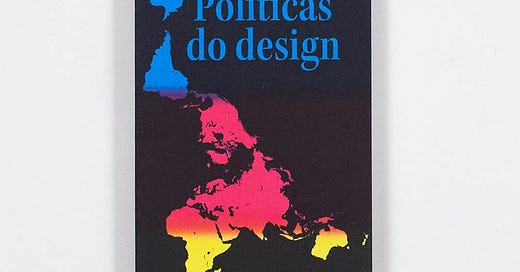
Tipo Aquilo #27 – Políticas do Design
A palavra “política” não deve ser usada de forma leviana. No nosso cenário midiático, cada vez mais polarizado, muitas pessoas dizem ter liberdade para serem apolíticas ou para ficarem de fora da política, como se existisse uma terra mágica para onde fosse possível fugir, sem sofrer o peso da opressão e da violência. Seria ótimo, mas infelizmente não existe um lugar assim.
Essa introdução faz parte da edição brasileira de “Políticas do Design”, de Ruben Pater, lançada pela Editora Ubu. A newsletter de hoje é uma espécie de resenha do livro, como pretexto pra falar aqui de toda a agitação social vivida no mundo, e alguns desdobramentos que acertaram em cheio até o mundinho da tipografia. Por ora, vamos ao livro.
A julgar pelo título, o leitor pode pensar que trata-se de um manifesto partidário de direita ou esquerda, disfarçado de guia de design. Ele não é. Também não quer dizer que ele seja um livro isentão ou simpático ao dois-ladismo. As políticas que aborda são as práticas e habilidades que o designer deve ter para projetar num mundo realmente global, atentando-se ao que ”global” significa de fato: uma grande civilização com várias religiões, idiomas, escritas, histórias, etnias e biomas vivendo num geoide. Por isso, ele aborda vários tópicos organizados entre os fundamentos da comunicação visual, e como esses tópicos funcionam em culturas diferentes.
Cada capítulo é breve — saltando entre erros, acertos e curiosidades de produção gráfica, branding e design digital — e o livro conta com várias adições e atualizações desde a primeira edição impressa. Com isso, ele consegue oferecer uma leitura rápida e assertiva em pouco mais de 180 páginas, e cada capítulo traz uma nova provocação sobre o que significa fazer design para um mundo global e menos centrado em Europa e América do Norte. É um primeiro passo interessante para uma conversa que estará mais frequente nos próximos tempos, a de descolonização do design.
Pense que o design, ao longo da história, cercou-se de um pensamento eurocêntrico que determina o que é design e quem pode dizer que faz design. O resultado é que, como vários campos de conhecimento, a história do design é um grande rolê de homens brancos. É difícil encontrar referências negras de design, por exemplo, e também é difícil que sejam entendidas como design outras atividades de produção e expressão visual em série feitas fora das capitais econômicas. Deveria ser mais fácil hoje, mas estamos em 2020 e ainda falamos de gente que quer estipular como e quando quer ser mais tolerante a diversidade.
Percepções baseadas em estereótipos de outras culturas também são maus exemplos na tipografia. Um exemplo é a Neuland, fonte criada em 1923 pelo alemão Rudolf Koch como uma versão moderna de escrita blackletter. Essa fonte tornou-se uma escolha comum para embalagens de cigarros e letreiros de circos, dando à fonte uma conotação “exótica” e “selvagem” o suficiente para que uma releitura de escrita gótica alemã pareça uma tipografia étnica africana. Enquanto a comunidade afro-americana produzia revistas e capaz de jazz usando fontes convencionais, os brancos ainda se divertiam com seu pastiche de arte africana, e reforçavam estereótipos com tipografias étnicas também com chineses e árabes.
Quem se envolve com ativismo no design muitas vezes trabalha em estúdios comerciais durante o dia e cria memes e imagens ativistas à noite. Não se trata de um caso de esquizofrenia, como se o designer se dividisse entre uma personalidade política e outra apolítica, mas sim de uma tática de sobrevivência para manter a saúde física e mental. Não dá para separar o design da vida pessoal, da mesma maneira como não dá para separar o design da política.
Algo que o livro aborda em vários exemplos, mas muito designer ainda sai da academia sem esse conhecimento, é que mesmo as menores decisões tomadas num processo de design são políticas, porque as relações humanas são essencialmente políticas. Escolhas de cores, fontes, redação, imagens, materiais e meios, são tomadas com base em vieses bem definidos e alinhados aos valores de pessoas e/ou organizações que visam influenciar e persuadir outras pessoas. Isso é política tanto quanto são as decisões de políticos que interferem no design. É discurso feito em imagem. Num mundo em que decisões políticas mudam até a forma de escrever de um país inteiro, dizer que política e design são dois entes separados e imiscíveis é ignorar o poder dessa retórica.
E as políticas do design não se resumem a tudo do estúdio pra fora; também dizem respeito a como o design é feito do estúdio pra dentro, de como as empresas criativas têm reagido (mal) às iniciativas de promoção de diversidade e denúncias de assédio no trabalho, e de como funciona a empatia necessária para trazer conhecimento de fora e ser mais inclusivo. Estúdios de design, agências de publicidade e associações de designers têm processos que refletem as relações de poder do lado de fora; por isso, esses lugares não podem admitir que estas relações de poder naturalizem quaisquer formas de discriminação.
Embora eu tenha tocado em outros assuntos e abordado pautas recentes, eu creio que não deixei de falar do livro em momento algum. O livro não se preocupa com o quanto ele expõe verdades tomadas como convenções do design, e com quanto o leitor está disposto a abrir a mente antes, durante e após a leitura. Não é um livro sobre ativismo no design, mas é sobre as consequências de um design preguiçoso, voltado a reafirmar valores antigos, e que diz que não se importa com política.